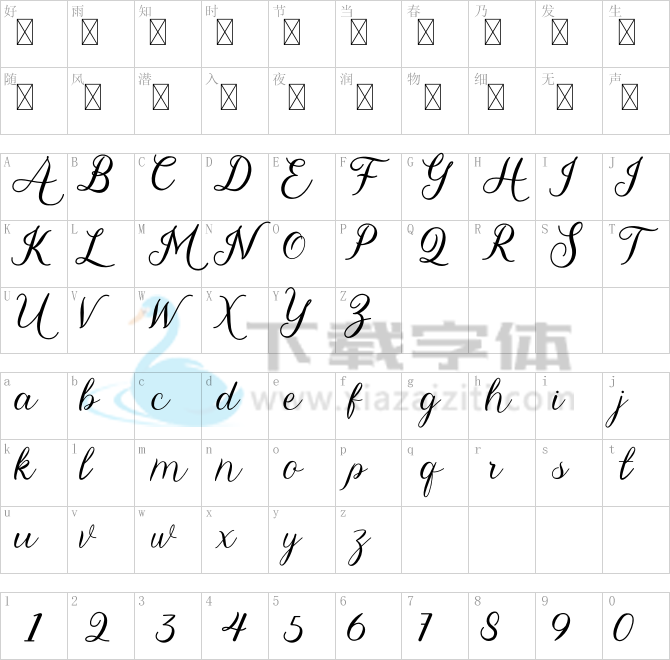
Abilane Free Trial.ttf字体下载,这款字体结构工整、笔画清晰,兼顾美观与易读性,适用于标题、正文、海报、包装、LOGO 等多种场景。字形优雅稳定,风格百搭耐看,适配日常排版与创意设计,让文字呈现更舒适、更具质感。Abilane Free Trial.ttf字体下载一笔一画,皆是细节,以均衡的比例、流畅的线条打造舒适视觉体验,字形端正大气,风格简约现代。无论是商业设计、品牌宣传还是日常排版,都能轻松驾驭,让文字更有格调与力量。Abilane Free Trial.ttf字体下载字体下载。